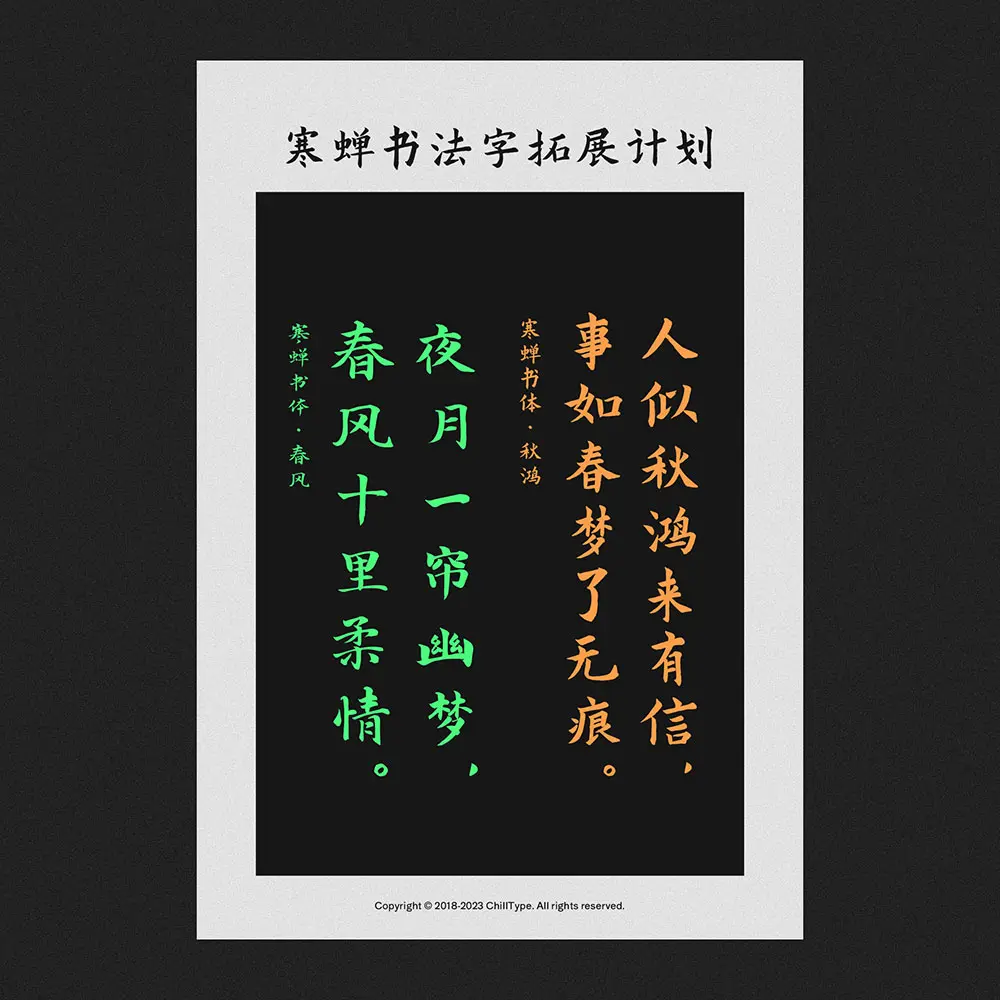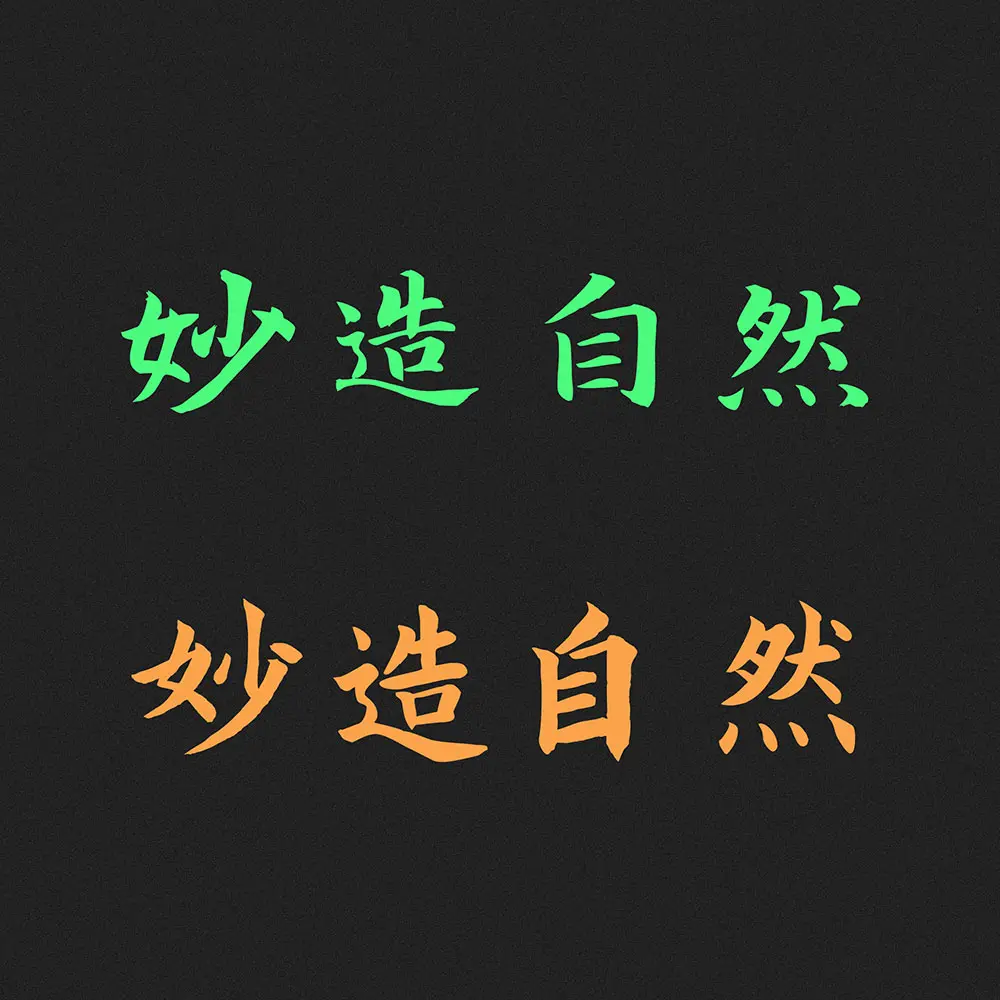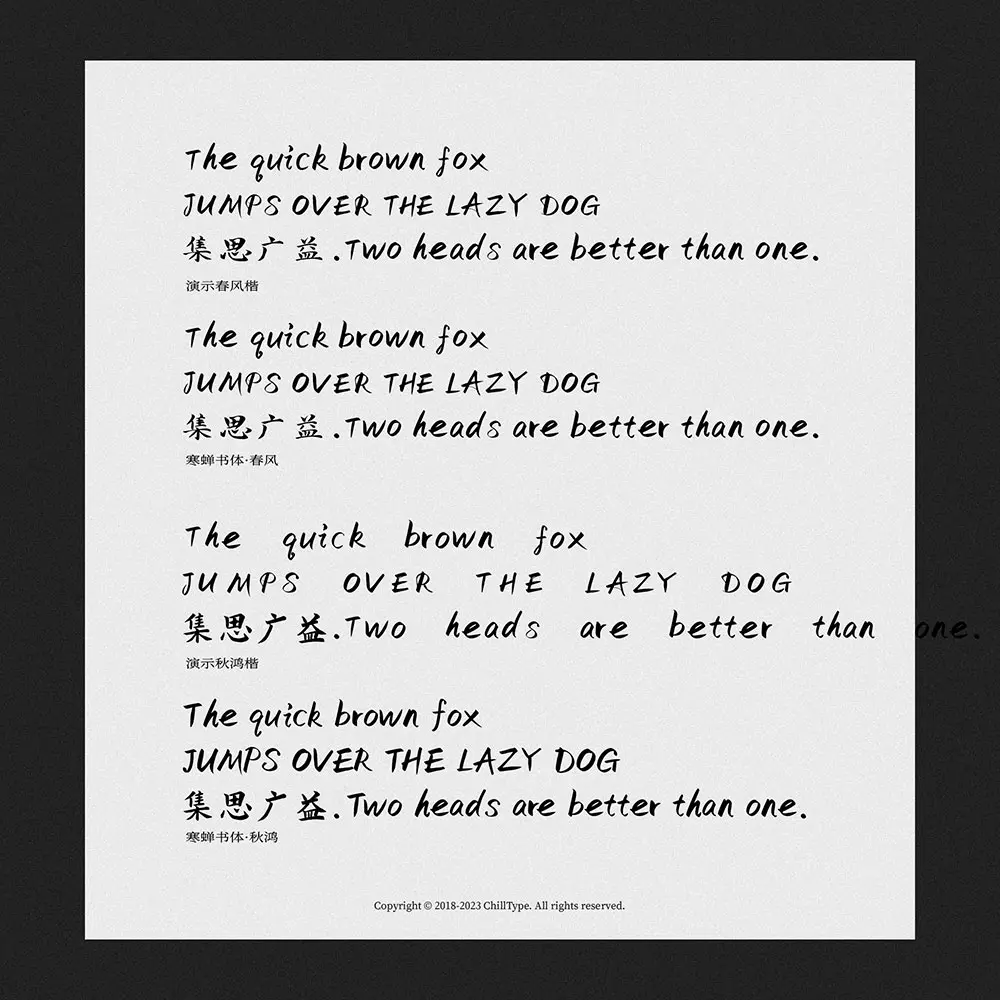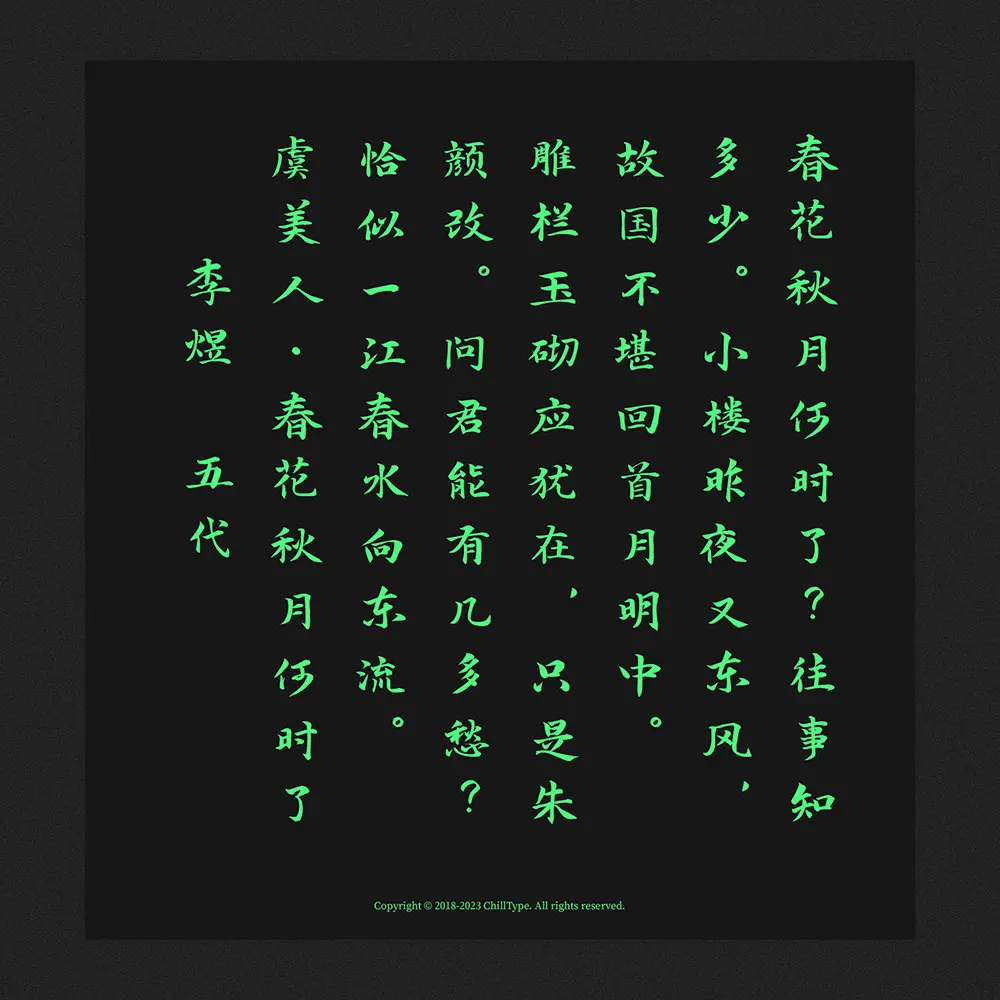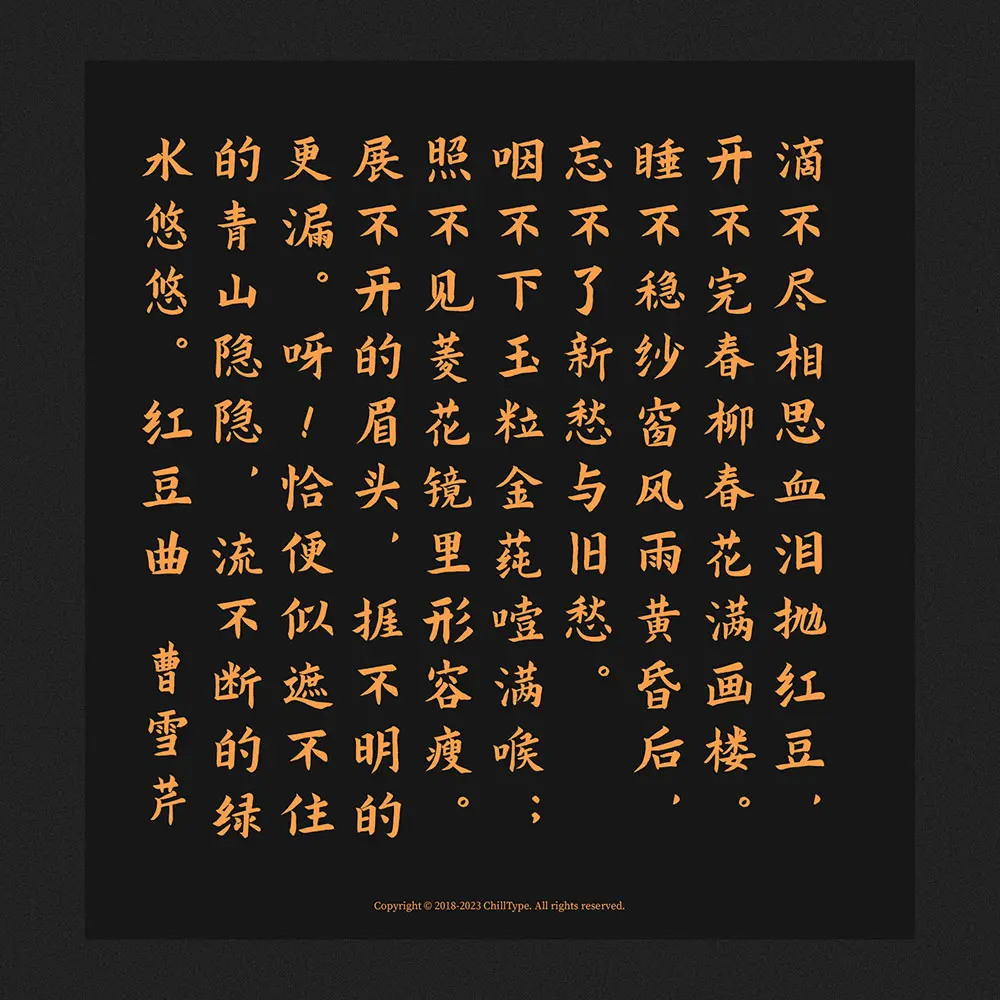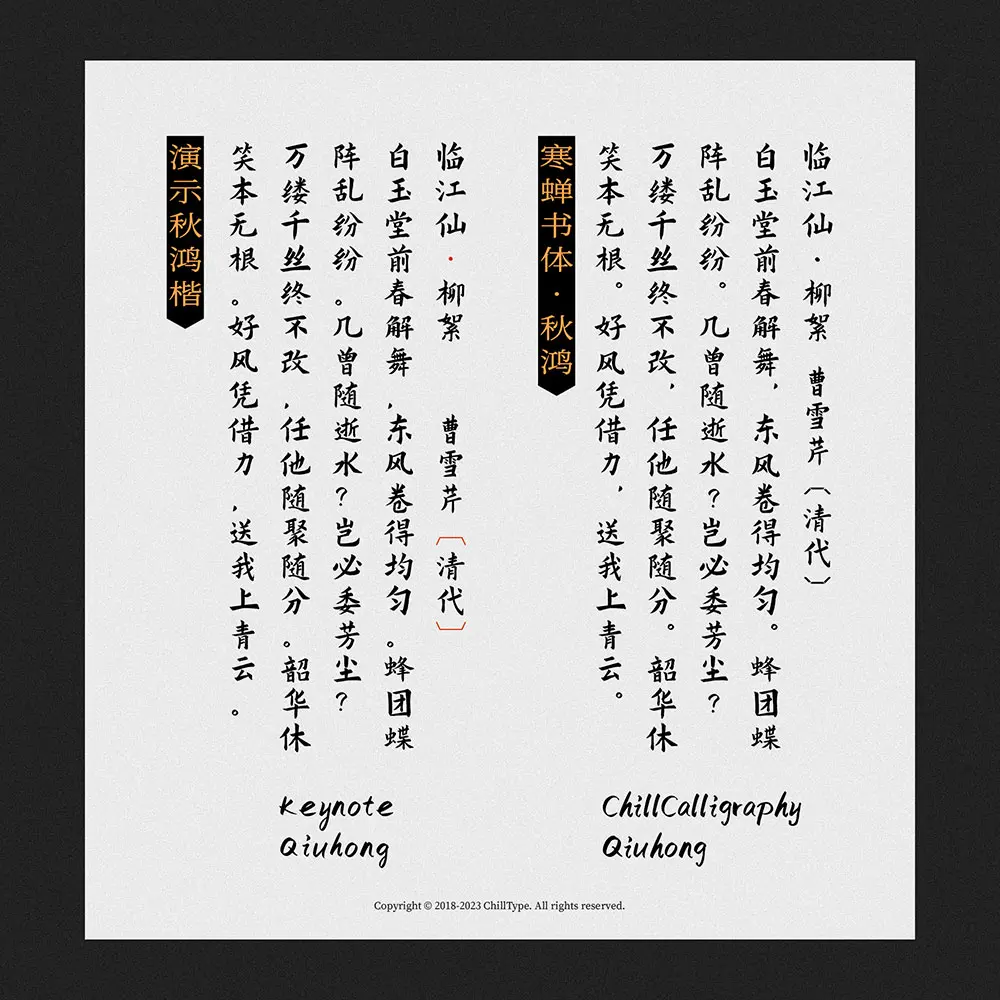
寒蟬書體 春秋預覽
寒蟬書體 春秋介紹
寒蟬書體_春秋是基於開源字體“演示春風楷、演示秋鴻楷”的拓展字形
春風 更新提要
調整西文字符及數字大小更加均衡。
調整部分字符忽高忽低的問題。
調整西文字偶距,優化橫向排版。
優化豎向排版。
新增 囉 瞭 舖 三字補全一級規範通用字。
新設計的.notdef,補充一些標點符號。
秋鴻 更新提要
調整西文字符及數字大小更加均衡,去除連筆和文字風格更接近,調整粗細。
調整部分字符忽高忽低的問題。
調整西文字偶距,優化橫向排版。
優化豎向排版。
新增 隹 囉 瞭 舖 啫 五字補全一級規範通用字。
新設計的.notdef,補充一些標點符號。